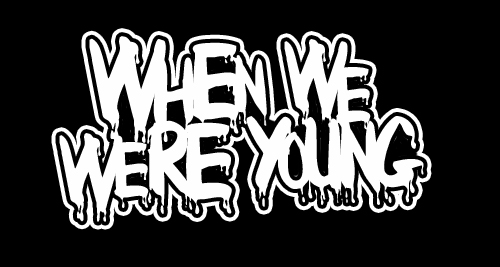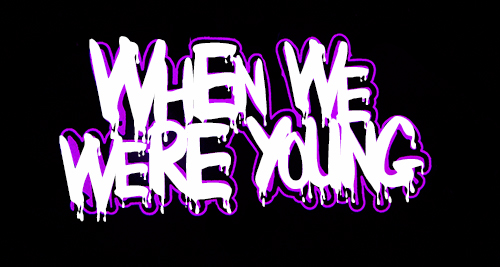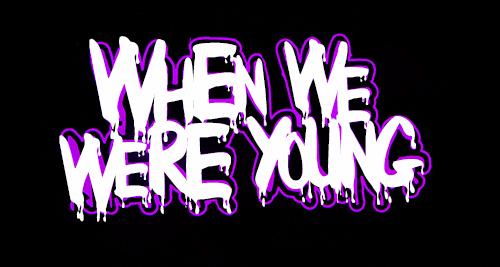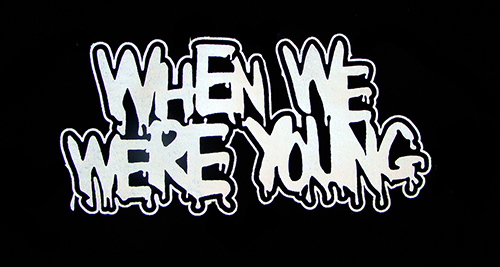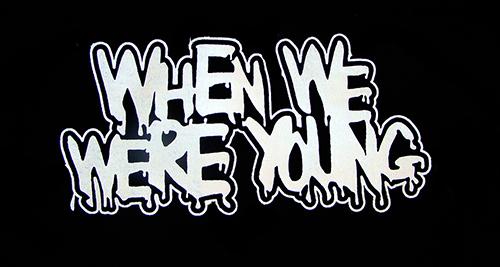
Eine Horror/Gore/Splatter-Schriftart gesucht bzw. ist das überhaupt eine Schriftart?
über Plattformen wie What The Font und ähnliche bin ich nicht fündig geworden. Dafür ist meine Grafik vielleicht zu speziell. Da einige Buschtaben sehr ineinander verfließen, weiß ich auch nicht, ob das so eine reine Schriftart ist ob eine Schrift noch weiter manipuliert wurde.
Ihr seht das Logo einer Party. Ich habe vom Organisator nur JPGs bekommen und er hat keine Infos, wie diese Grafiken entstanden sind. Dahinter verbirgt sich kein großes Unternehmen, es ist nichts regionales oder saisonales. Daher weiß ich nicht, welche weiteren Angaben ich noch machen könnte.
Meine Suche nach Horror/Gore/Splatter-Fonts war nicht erfolgreich. Kann mir jemand helfen?
Mir schaut das nicht nach einer Schrift aus, dafür sind gleiche Buchstaben einfach zu unterschiedlich, selbst wenn dafür irgend ein Font, wahrsxcheinlich ein Freefont Pate gestanden haben mag.
Wenn du jedoch nur dieses Logo brauchst, ist es am besten, das Bild zu vektorisieren. Ich hab das mal schnell gemacht:
Meinst Du? Diese Tropfen z.B. scheinen bei allen E an gleicher Position vorhanden zu sein.
Beim W auch und die Schrift sieht ein kleines bisschen nach der OPTI Dracula aus.
Es gibt also sehr wahrscheinlich sehr ähnliche bis identische Schriften mit anderen Namen.
Die ähnlichen Schriften kannst u.U. Du mit den Lettern aus der Opti Dracula und einer Anfrage an die Schriftensuchmaschine Deines geringsten Misstrauens finden.
Vielen Dank für die Hilfe! Die Opti Dracula sieht sehr passend aus. Wenn ich die Buchstaben einzeln setze und nicht als Fließtext sollte das passen!
Beim verfassen dieses Beitrages ging im trotz kleiner Zweifel doch von einer Font aus. Zwar sind die W's und E's unterschiedlich groß aber in sich meiner Ansicht nach doch identisch.
Ich habe aber bei Myfonts.com keine kommerzielle Schrift gefunden die die Basis für die Opti Dracula sein könnte. Identifont.com liefert bei einer ersten, oberflächlichen Suche nach Stichworten auch nichts. Bliebe also nur noch eine Bildersuche und dazu bin ich gerade zu faul. Aber vielleicht hat einer der Mitforisten noch zielführende Informationen?
Dafür gibt es schamlose und unvollständige Kopien von der ehemals kommerziellen Opti Dracula. Warnung! Diese Beispiele dienen nur der Abschreckung! Lasst diese bitte auf den Servern.
Bei Dafont in der Rubrik Extravagant -> Horror "Bloody":
Bei Abstractfonts in der Rubrik Bloody "Wet Paint":
Möglicherweise wurde der Schriftzug in der Opti Dracula oder einer ähnlichen Schrift (siehe Hinweise im anderen Posting auf zwei weitere Billigsabklatsche *) gesetzt, dann der Schriftzug in Vektoren umgewandelt und diese einzeln verschoben sowie nachbearbeitet. Sehr wahrscheinlich wurde irgendwann mal bei der Bearbeitung auf Strichdicke verbreitern geklickt. Mit Inkscape sind das nur sehr wenige Schritte. Probiere das mal aus und Du wirst ein sehr ähnliches Ergebnis erhalten.
*)  Meine Vermutung währe das Wet Paint oder Bloody eher verwendet wurden als das wenig bekannte Original der Opti Dracula. Aber das ist nur noch von akademischen Interesse und nicht praxisrelevant.
Ich habe nun die ursprüngliche Grafik genommen und mit Opti Dracula die Buchstaben einzeln drüber gesetzt und eben entsprechend angepasst. Und siehe da, bis auf das W und ein paar Kleinigkeiten passt es sehr gut, wie ich finde. (Datei: WWWY-Vergleich-Alt-Neu - Opti Dracula ist weiß und in rosa im Hintergrund ist das alte Logo).
Mit den Umrandungen habe ich es dann auch nochmal mit Opti Dracula probeweise erstellt und bin damit schon ganz zufrieden.
Und nun noch eine Frage für mein Verständnis: Auf der Seite http://opti.netii.net/fonts-d/index.htm kann ich die Schriftart herunterladen aber ich darf sie nicht kommerziell nutzen, richtig?
ok, danke dir, dass du meine Vermutung bestätigst. Das Logo wird so schon lange verwendet aber da ich nun gebeten wurde, das neu aufzulegen bzw. da es nur noch JPGs gibt, wollte ich es nun einmal richtig machen und versuche so gut es geht alle Infos zusammen zu tragen und es auch rechtlich sauber zu machen, wenn wir es eh schon neu machen.